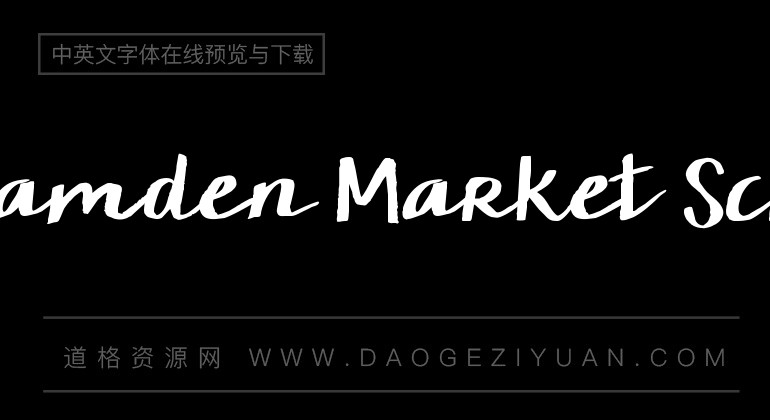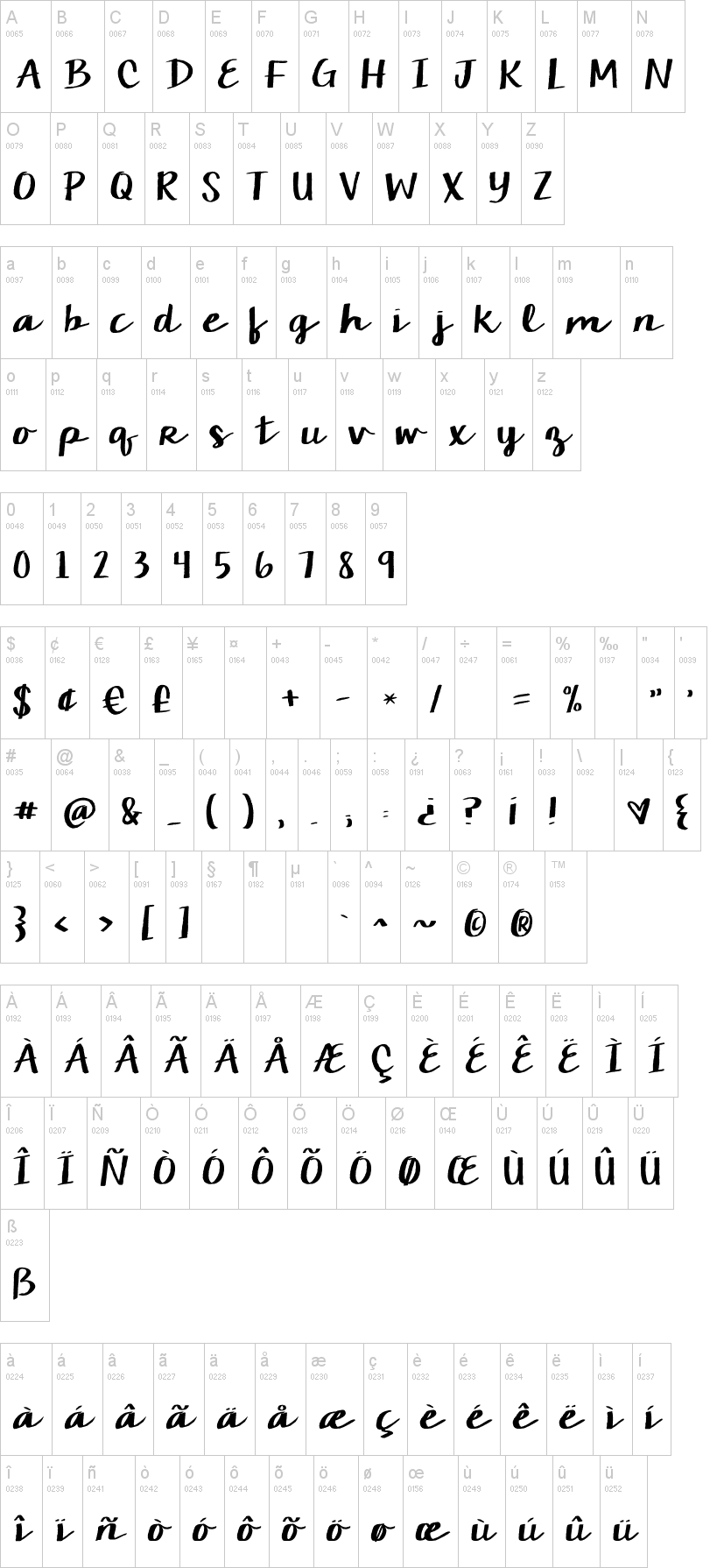
KG Camden Market Script 是一款由 Katie Garner 设计的手写脚本字体,它具有流动、柔和的设计,能够提供现代、温暖的感觉。这款字体采用了细腻的笔画,具有细节丰富、活力四射的效果,可以用于各种海报、标识、卡片、礼品等应用场景。KG Camden Market Script 具有良好的可读性,能够为文字提供清晰的印象,并且可以轻松地与其他字体搭配使用,从而营造出精致的设计效果。内容介绍
KG Camden Market Script是一款非常不错的手写艺术字体,具有很好的视觉感,适合于文化类的宣传设计、商业类品牌的广告和产品包装设计以及个性化文字排版等较多场景。